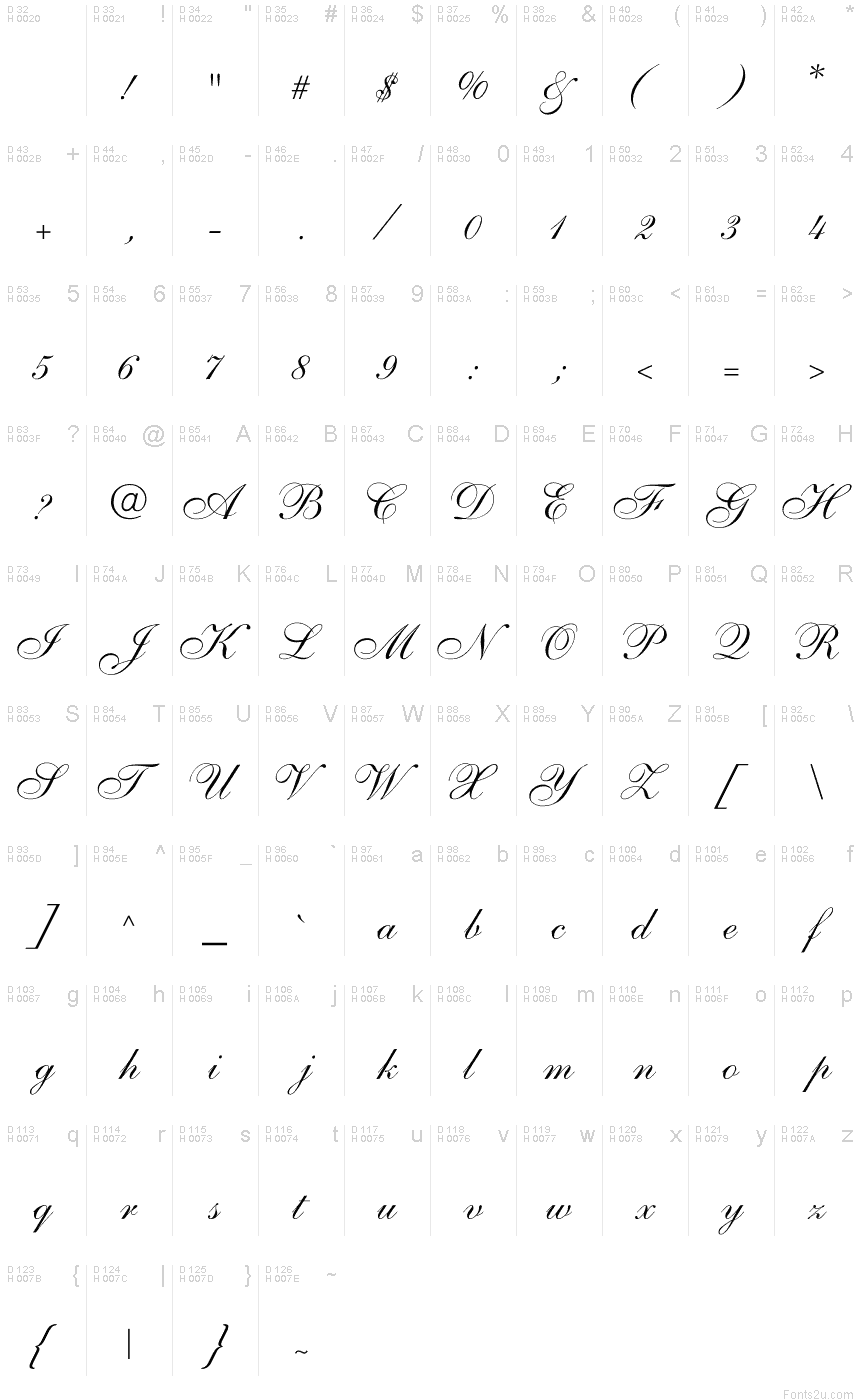
Allegro — это бесплатный каллиграфический шрифт с размашистыми росчерками и элегантным, контрастным ритмом. Его резко восходящие штрихи, тонкие линии и свободные петли напоминают классический почерк, сохраняя при этом живость и выразительность букв.
Плавные линии создают изящный акцент в свадебных приглашениях и праздничной полиграфии, где удлиненные элементы могут гармонично сочетаться с рамками или цветочным декором. Этот бесплатный шрифт также придает утонченность упаковке косметики, фирменному стилю бутиков, обложкам изданий и личным монограммам, особенно если в дизайне достаточно «воздуха» для его драматичных форм.
Allegro